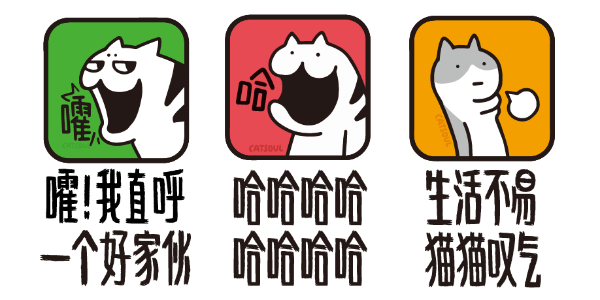
一款好看又好用的漫画字体
汉仪喵魂漫画体 | 好看好用的漫画字体
汉仪喵魂漫画体是由汉仪字库签约作者、漫画家喵魂Catsoul创作的第三款字体作品。这款字体继承了喵魂老师一贯的轻松诙谐的手绘风格,运用笔刷写就的笔画,绘制出这款充满漫画风格的字体。这款字体风格独特、实用性强,即可充当标题,也可以用在部分短文案场景。该字体适合用在绘本漫画、儿童用品、视频海报等娱乐感、漫画感强的场合。
汉仪喵魂漫画体 | 字形修长明显
汉仪喵魂漫画体字形极其修长,接近汉字窄体的极限。笔画被均匀地填充在矩形方框内,使得字形饱满富有冲击力。
为保证字体能够被填充进狭长的矩形框并且识别度良好,这款字体被制作成变宽字体。字形宽度会随着字形的特性与复杂程度而变化,这使得字形的细节能够得到更加充分地展示,排版起来更加生动流畅,符合日常书写规律。
汉仪喵魂漫画体 | 笔画生动有趣
这款字体笔画的绘制灵感源自游戏手柄上的图形符号。作者将这四个符号融入到笔画绘制中,使得字形看起来生动有趣充满节奏感。
作者用独特的笔刷绘制出这款字体,笔画起笔收笔处有着邮票边缘一样的花边,笔画内部有着笔刷刷过形成的独特飞白,这些丰富了字体的细节,使字体更接近漫画感。
字体中的“口”字结构,会根据不同字形的特性进行调整,时方时圆,使得字体灵动又整齐,风格上介于严肃与活泼之间的状态。
汉仪喵魂漫画体 | 中西文匹配
这款字体的西文部分也是由喵魂老师亲笔绘制,字形高挑修长富有气质,中西文混排风格一致,搭配和谐。
汉仪喵魂漫画体 | 展示样张